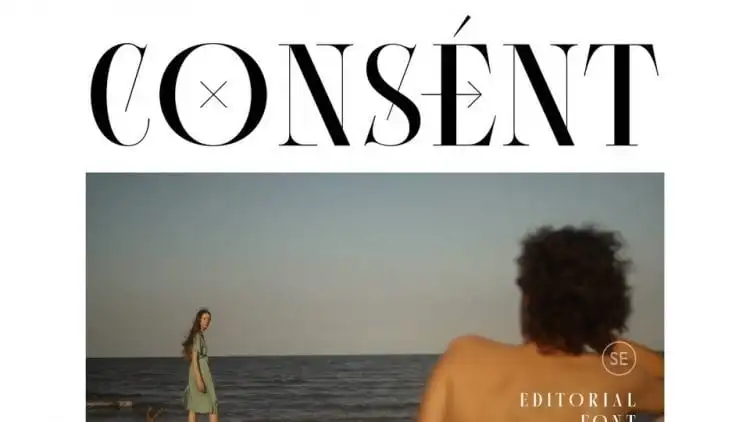
Consent Serif Font – Download Grátis
Consent Serif é uma elegante fonte serif que foi criada por saridezra com um toque vintage e mágico. Seu design clássico e sofisticado torna esta fonte perfeita para estilos modernos de webdesign, especialmente aqueles buscando algo único em seus projetos. Suas características especiais garantem que sua identidade seja única e se destaque entre a multidão. É uma escolha perfeita para aplicativos que exigem um toque personalizado no design de cartões de visita ou sites, tornando seu trabalho ainda mais memorável.